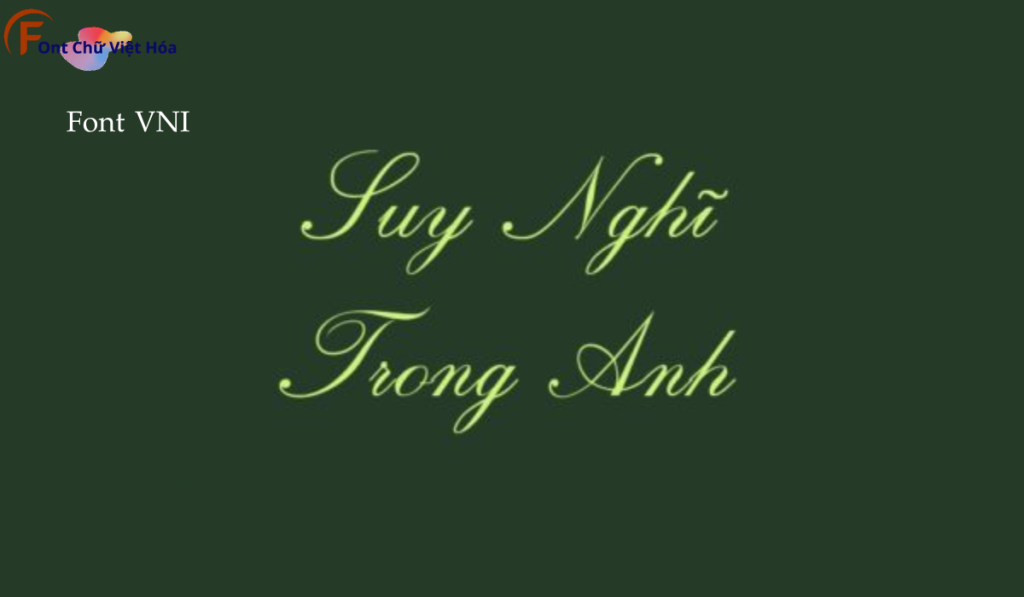
Font VNI Script Việt Hóa
Tác giả: VNI Script
Bộ Font: Font VNI
Kiểu chữ: Chữ viết tay
Font VNI Script Việt Hóa, thuộc bộ font VNI, mang phong cách viết tay mềm mại và tinh tế, lý tưởng cho các dự án thiết kế như thiệp mời, bìa sách, và các sản phẩm thủ công. Với các nét chữ uyển chuyển và độ dày đều đặn, Font VNI Script Việt Hóa không chỉ dễ đọc mà còn tạo cảm giác nghệ thuật và thanh lịch. Việc Việt hóa font giúp người dùng dễ dàng tích hợp vào các thiết kế tiếng Việt, mang lại sự tiện lợi và nâng cao tính thẩm mỹ.